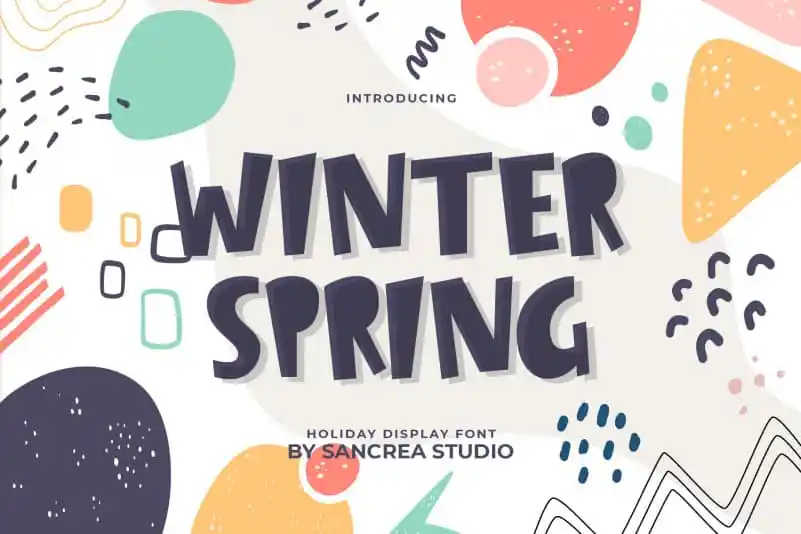
Winter Spring Display Font – Download Grátis
Winter Spring Display Font é uma elegante escolha para aqueles que procuram destaque na comunicação visual nessa época do ano especial. Essa fonte de destaque para ocasiões festivas traz letras divertidas, quirkies e descontraídas, ideal para criar um ar enérgico e alegre em qualquer aplicação. Como seu nome sugere, é uma fonte em caixa alta que faz um ótimo trabalho em headlines e títulos de página. Seja para aniversários ou festas de fim de ano, esta fonte oferece o toque especial que você precisa para destacar seu design. E embora seja chamada Winter Spring, sua versatilidade não está limitada a estas épocas específicas; ela pode ser usada em qualquer aplicação onde um pouco de criatividade e diversão são bem vindos.